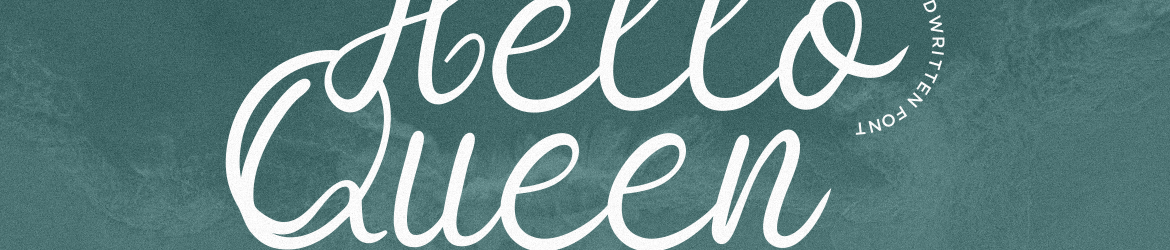
Hello Queen Font – Download Grátis
A “Hello Queen Font” é uma elegante e delicada tipografia script criada para aqueles que buscam uma aparência refinada e renovadora em seus projetos visuais. Essa fonte foi especialmente concebida para pessoas que desejam dar um toque de frescura a seus designs, trazendo sofisticação ao seu estilo visual sem comprometer a sua personalidade única. Com traços finos e linhas suaves, essa font oferece uma maneira perfeita de introduzir elegância em qualquer layout ou design gráfico, tornando-a um recurso indispensável para criadores de conteúdo que buscam um ar descontraído e versátil sem deixar de lado o brilho e a classificação.